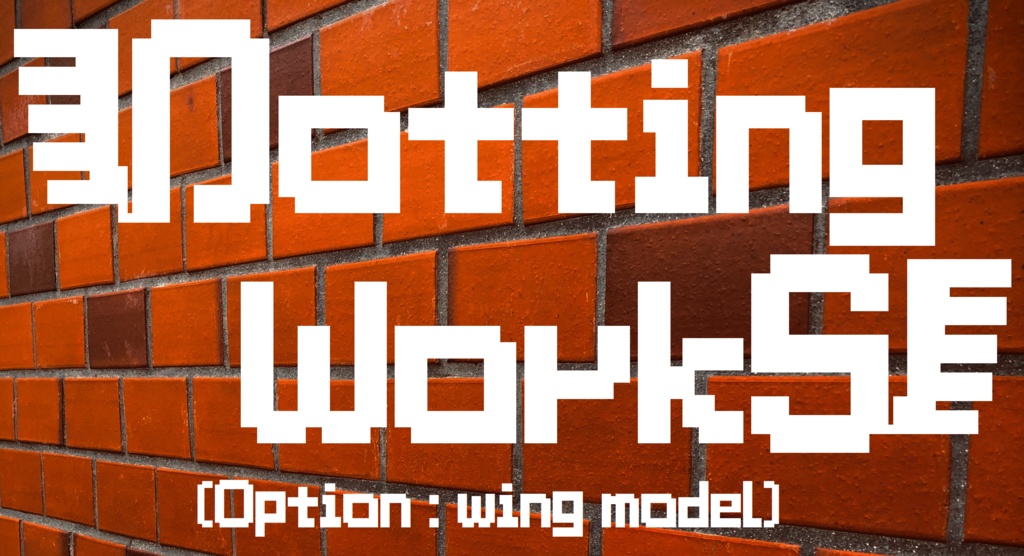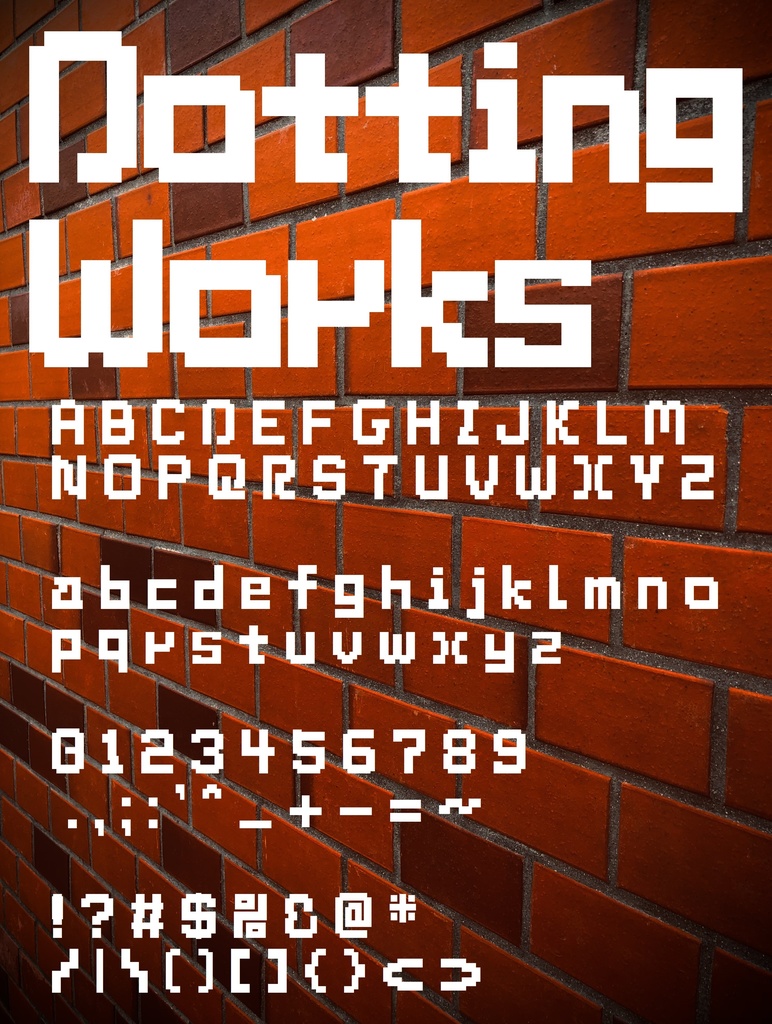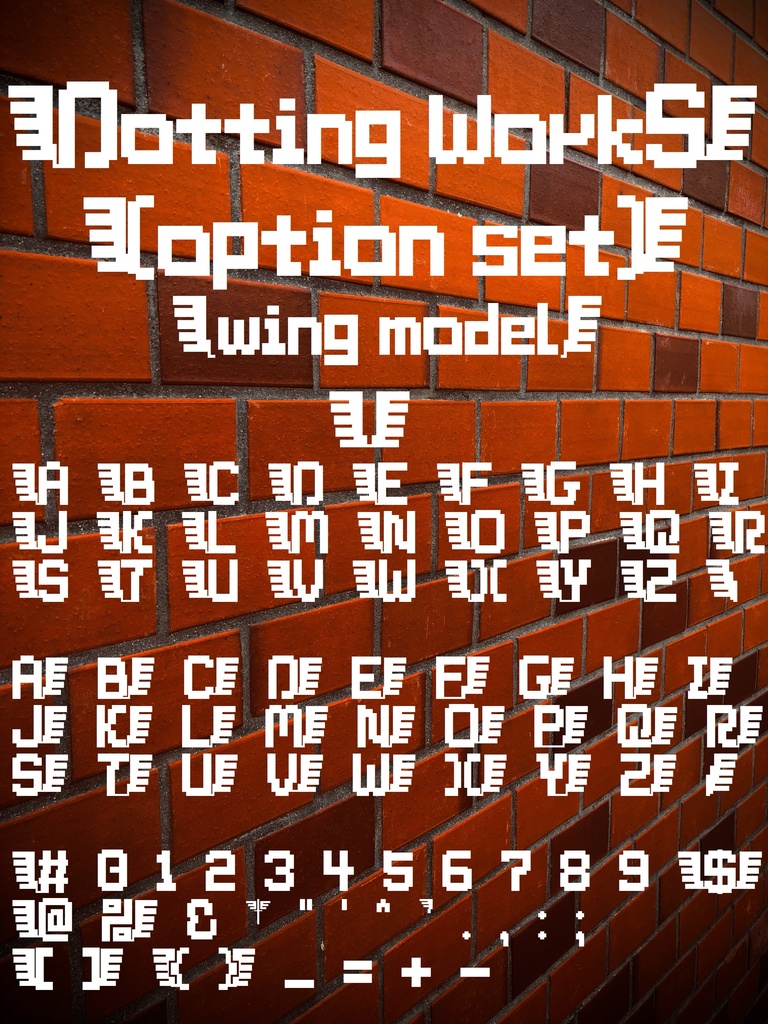
フォントデータ”Dotting Works Option Set”
"レトロ調ドット絵"をイメージしたフォント"Dotting Works"に、"はね"をイメージした飾り文字の"オプション"を追加したセットです。 「TrueTypeフォントファイル」という形式です。 ダウンロードした後、Zipファイル内のデータをインストールしてお使いください。 本製品は"Dotting Works"と"Dotting Works Option-Wing"の、2つのフォントデータのセットとなっております。組み合わせてお使いください。 このフォントは商業利用可となっております。 お客様の制作・創作活動のお役に立てれば幸いです。 ※使用上の注意事項などは、添付のReadmeをお読みください。